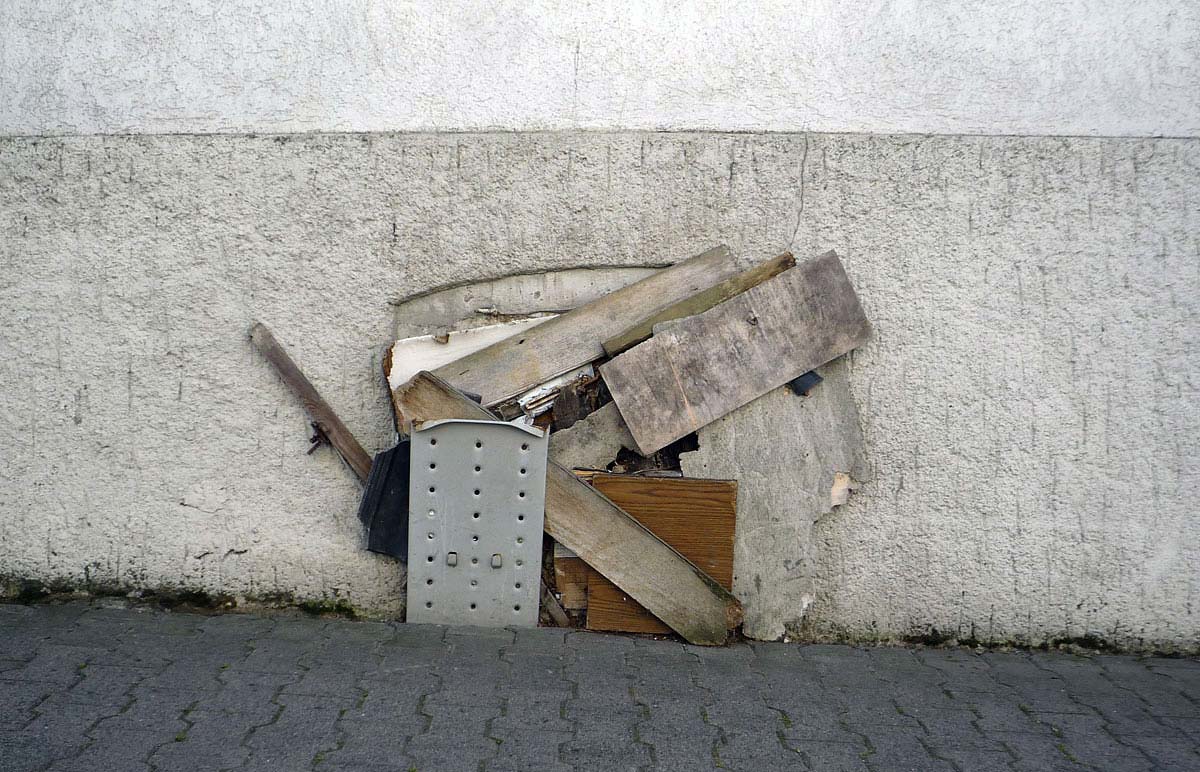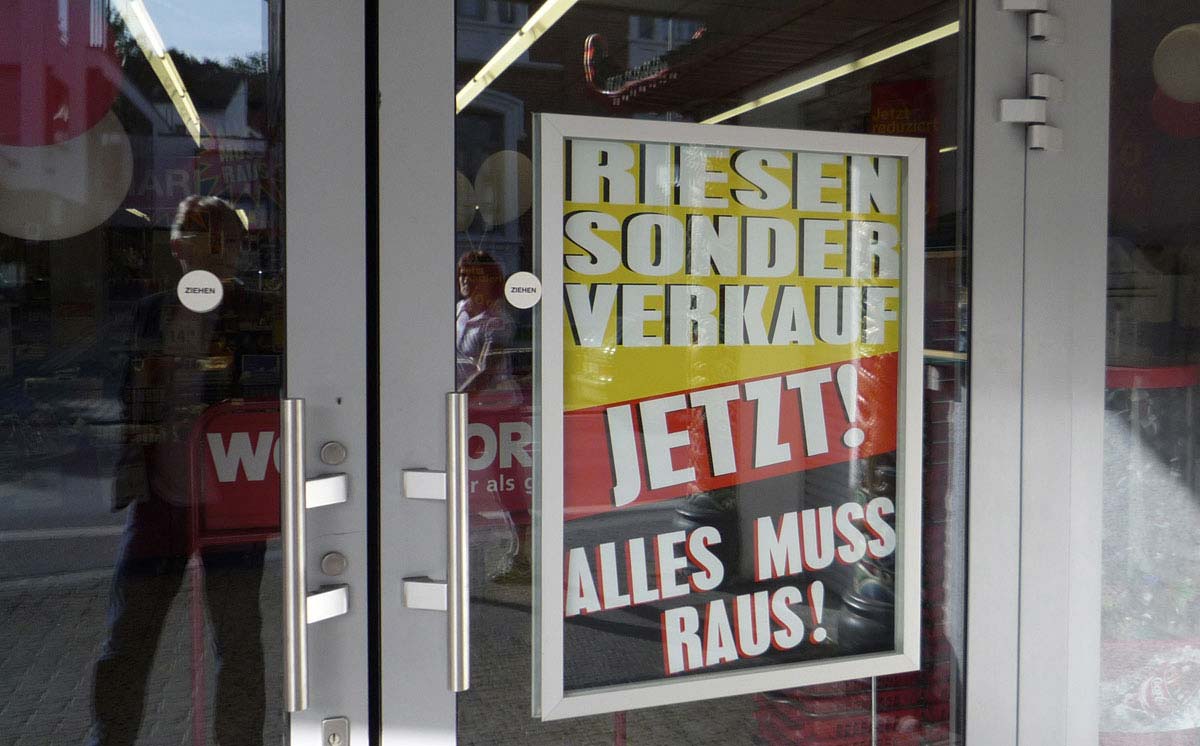
Unser Spaziergang beginnt im Feld, oberhalb meiner Heimatstadt. Mähdrescher der Marke John Deere ernten gerade Raps. Früher wurden hier Roggen, Weizen, Mais und Hafer angepflanzt, heute ist die Biodiesel-Pflanze die klare Nummer 1 auf den Äckern des Goldenen Grunds. Ich muss mich nicht bücken, um das beeindruckende Michelin-Logo auf dem 2 Meter hohen Traktorreifen zu fotografieren.
Betritt man das Städtchen über die Lisztstraße, stößt man am Mühlweg auf das Restaurant Casamar, das vorgestern geschlossen wurde. Trotz medialer Unterstützung durch die Kabel-1-Fernsehserie Hagen hilft (iTunes-Episoden-Link) gab der Wirt Jürgen Müller nach zwei Jahren auf. Er trägt es mit Fassung, für ihn ist das Kapitel Casamar Geschichte.
Ich glaube der Fall Casamar zeigt, dass ohne Kommunikationsdesign nichts läuft … da kann die Küche noch so gut und noch so günstig sein. Der TV-Unternehmensberater Stefan Hagen hat sich um die Speisen und die Positionierung des Restaurants gekümmert, aber nicht um dessen Namen, das Erscheinungsbild und die Werbung. Wenn man sich im Hochparterre eines Ärtzehauses in einer Kleinstadt einnistet, das nicht nach Gaststätte aussieht, muss man mit eindeutigem Namen und Signalen auf sich aufmerksam machen. Warum nicht »Zur Mühle«, denn die stand dort zuvor jahrzehntelang und das wissen viele Bürger der Stadt noch. Casamar versteht keiner, und wenn man es versteht, werden viele Einheimische den Kopf schütteln, denn Meereskost am Emsbach ist ziemlich weit hergeholt.
Völlig verunglückt: das übergeschnappte Logo, mit unlesbarem Namen, unverständlich in seiner Aussage. Am Haus funktioniert es überhaupt nicht. Wenn man davor steht fragt man sich »Wo ist hier ein Restaurant, bitteschön?«. Und so glaube ich, dass 90 Prozent in meiner Heimatstadt das Casamar gar nicht kennen, obwohl es direkt gegenüber der Post liegt.
Das Darstellungsproblem scheint der Wirt inzwischen gemerkt zu haben. Heute schreibt er auf seiner Webseite: »In nur zwei Jahren waren wir zu einem der besten aber immer noch wenig bekannten Restaurant der Gegend aufgestiegen!« Dann schimpft er noch ein bisschen auf jene Menschen, die er eigentlich bewirten wollte. Adieu, Jürgen Müller.
Ebenfalls im Mühlweg, kurz vor der Kreuzung mit der Bundesstraße 8, trifft man an einer ehemaligen Möbelfabrik auf ein kleines, sehenswertes Kellerfenster. Es wurde in den letzten Jahren mit alten Holz- und Metallplatten gesichert: jede Saison eine neue dazu, wie am Walk of Fame in Los Angeles. Große Kunst.
Wir biegen rechts ab in die B 8 Richtung Frankfurt. Dort liegt eine der letzten geöffneten Woolworth-Filialen im Land, doch auch sie wird bald schließen. Alles muss raus! Der Schlecker nebenan wird im September folgen, der Matratzenladen im selben Gebäude hat bereits vor mehreren Wochen die Segel gestrichen. Wenn Schlecker eine Immobilie verlässt, muss sie wirklich wertlos sein.
In einer Brache gegenüber erblüht neues Geschäftsleben, links ein Imbisswagen mit Vorbau, der uns neugierig machen möchte, daneben ein Marktwagen, aus dem heraus Backwaren verkauft werden. Davor vier Halteflächen für Kurzparker, was sehr wichtig ist, wenn man in meiner Heimatstadt ein Geschäft betreiben möchte.
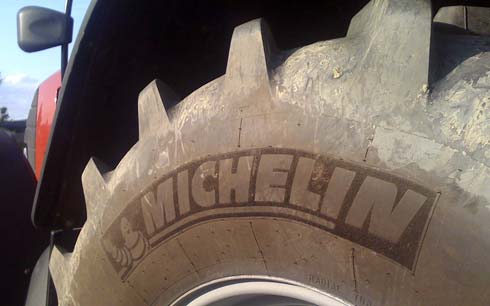
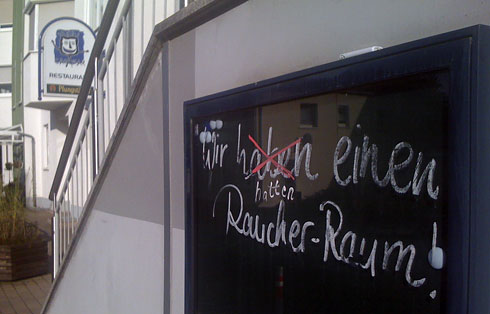
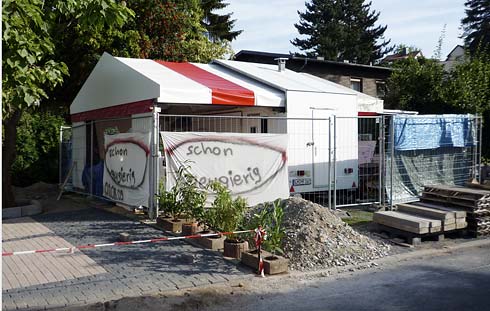
Das Logo sollte vermutlich einen total zugedröhnten Nikotinjunkie in einer blauen Dunstwolke darstellen :)
großartige doku, bitte mehr davon! kannst du nicht noch etwas mehr urlaub nehmen und für uns durch die provinz reisen? ;)
die beleidigungen auf der webseite von casamar sind echt der gipfel.
solange man lebt soll man rauchen
NichtMehrRauchen ist cool (seit knapp 4 Monaten) und die Type vom Casamar wird nichtmal mehr ne Stelle bei McDingens bekommen. Sorry, das geht mal gar nicht…..
Ehrlicher weise sollte man dazu sagen das Kommunikationsdesigner immer eine Ausrede haben warum etwas nicht funktioniert,
Währe statt dessen die “alte Mühle” pleite gegangen war dann eben das Konzept zu altbacken, unkreativ, man konnte einfach die jungen nicht erreichen, einfach schon wieder eine Dorfkneipe warum nicht was ausgefallenes?
Etwas das südlich klingt? Nach Meer?
Wie währe es mit Casamar?
:-P
@robertmichael: Deine Arbeit für das Brauhaus Pirna »Zum Gießer« zeigt, wie man es richtig macht und wie wichtig die visuelle Begleitmusik für den Erfolg einer Gaststätte ist.
danke jürgen. wobei ich auch sagen muss, alles steigt und fällt mit der leistung und dem service des hauses. wenn das essen nicht schmeckt und der service nicht funktioniert, da kann die werbung noch so gut sein – keiner würde das haus je wieder besuchen. bei casamar sah es so aus als wollte man etwas sein was man nicht ist. schuster bleib bei deinen leisten. erst wenn das produkt stimmt, zahlen die kunden auch gerne mehr dafür.
da finde ich den imbisswagen (oder ist das ein pavillion?) im letzten bild schon viel ehrlicher. hier weiss ich was ich bekomme und wenn es mehr wird als erwartet (hey, der hat kundenparkplätze! ;)) dann freue ich mich und komme gerne wieder.